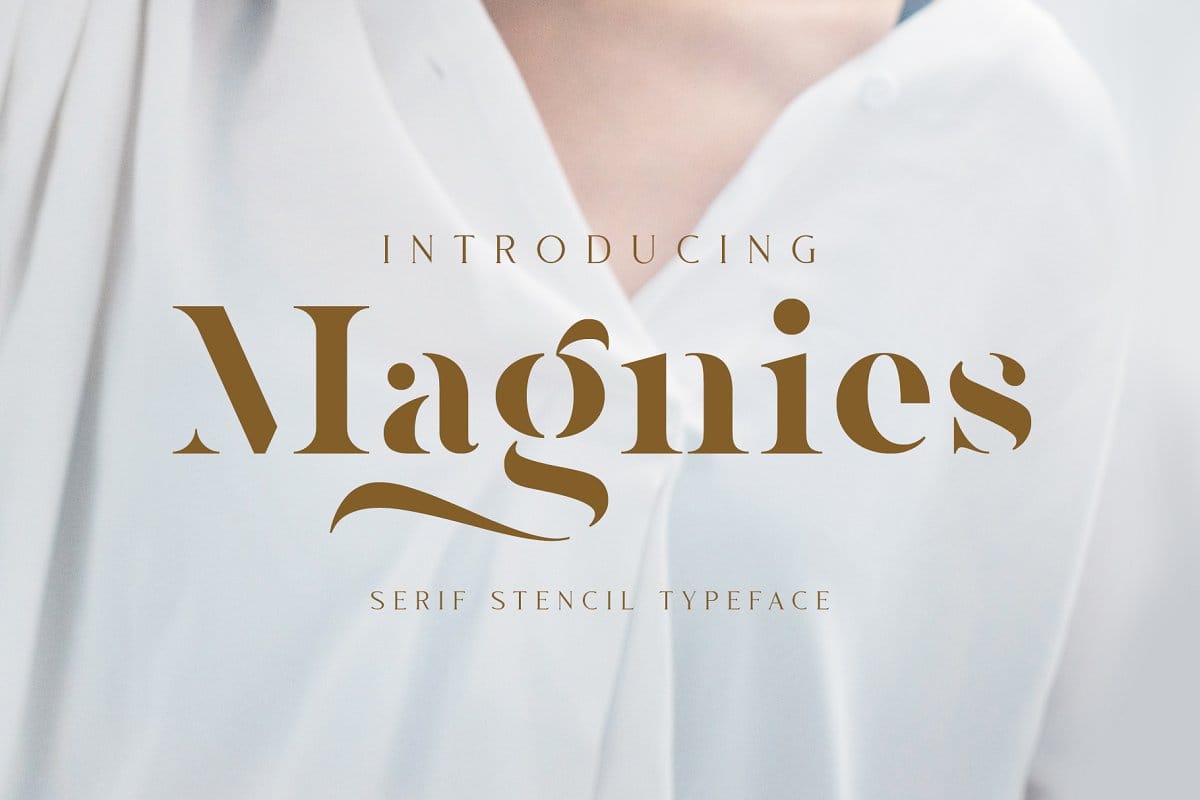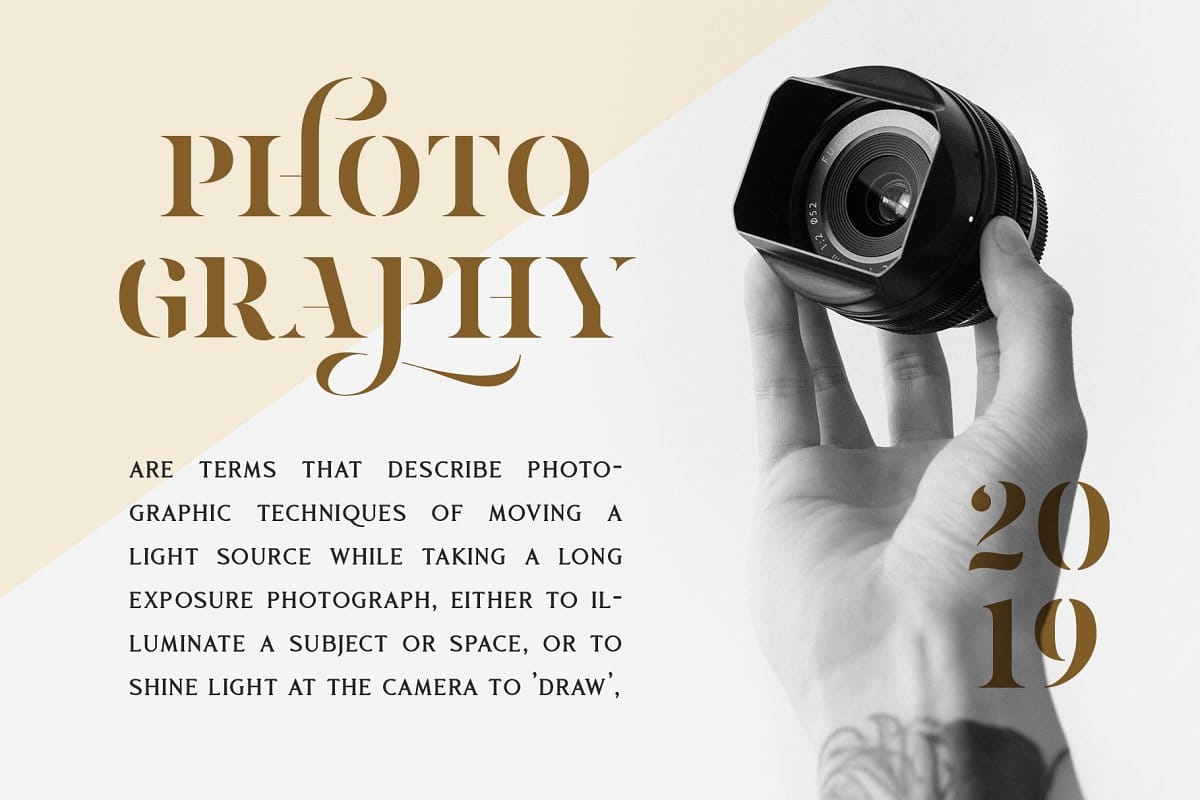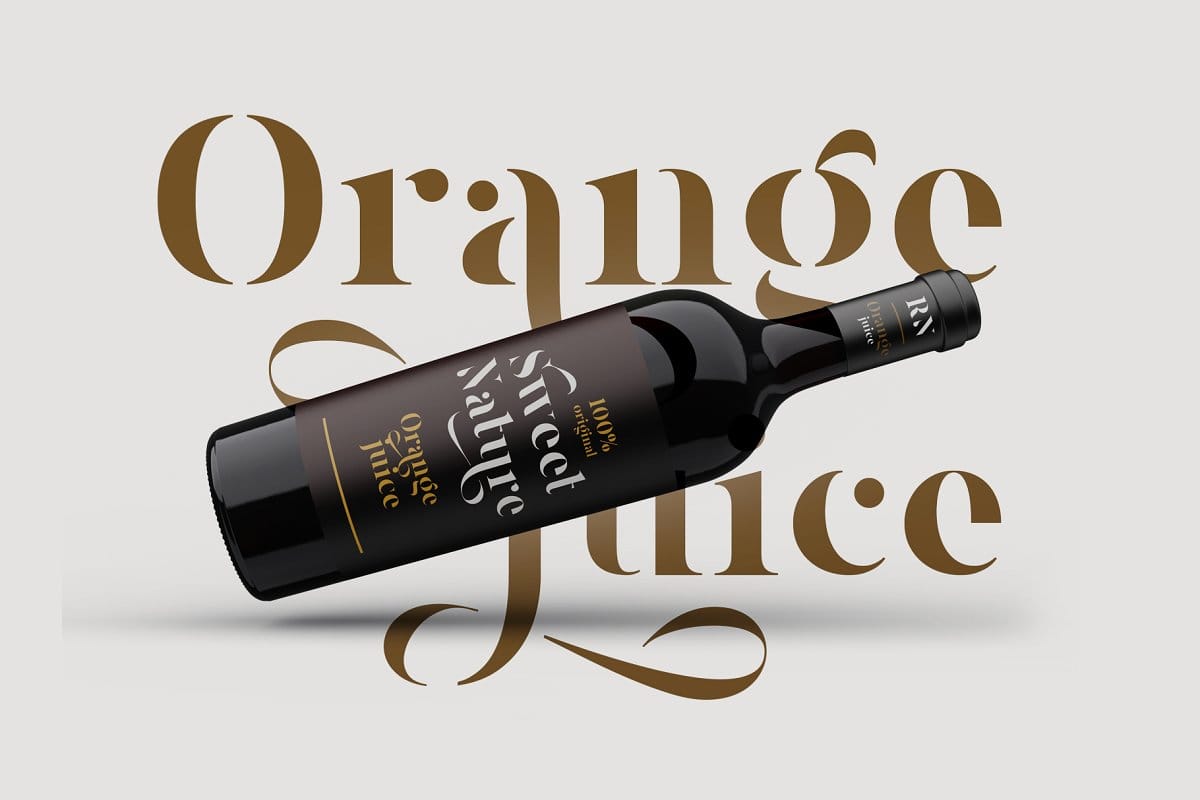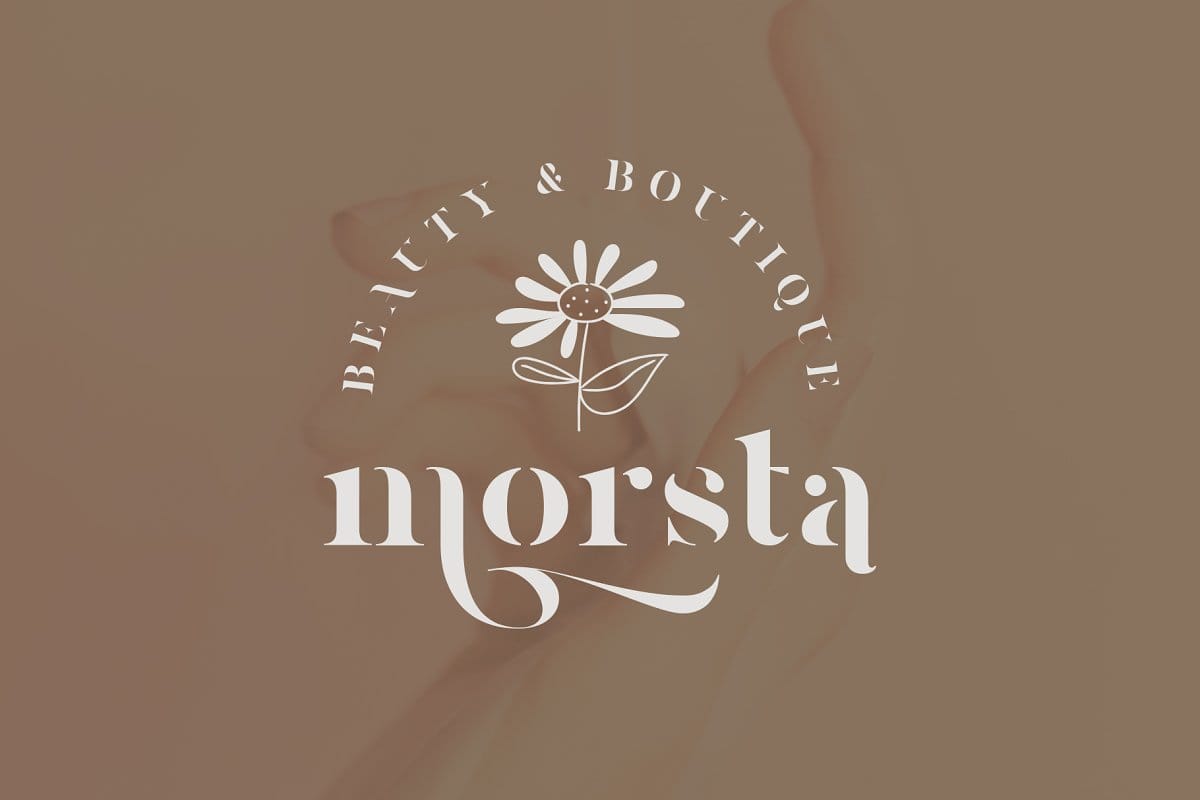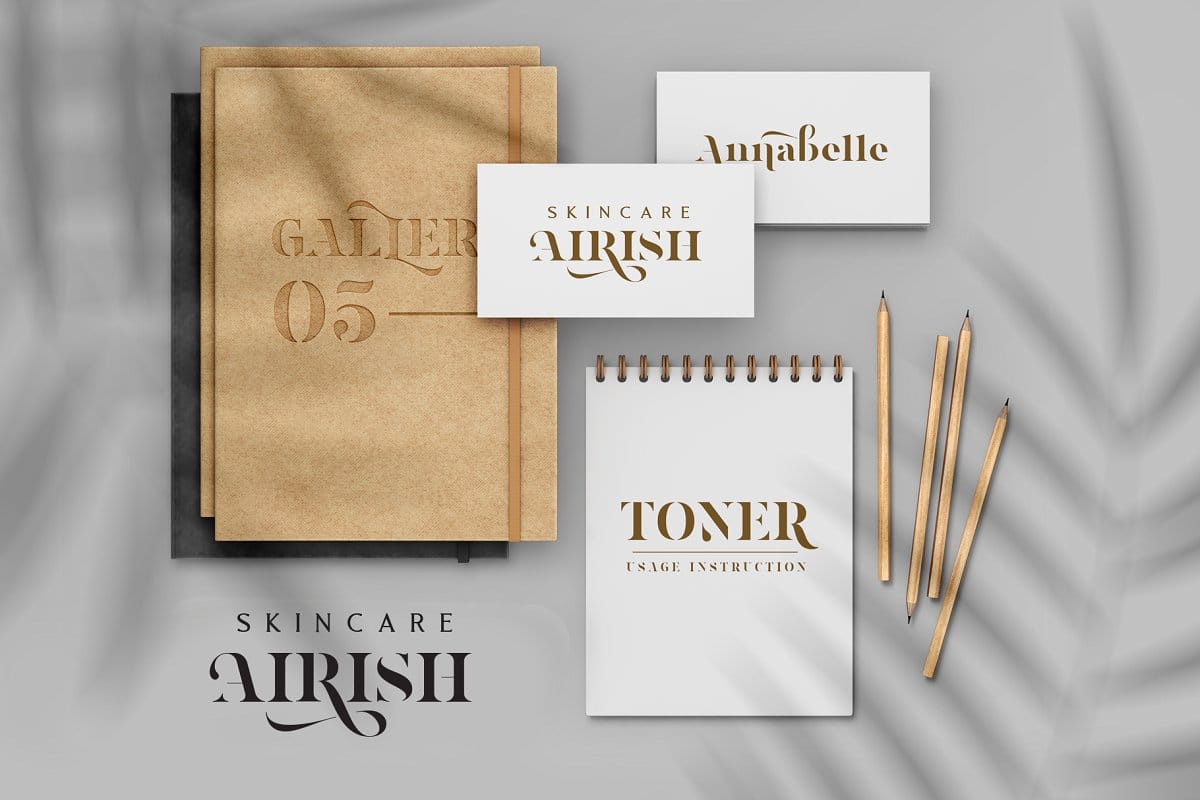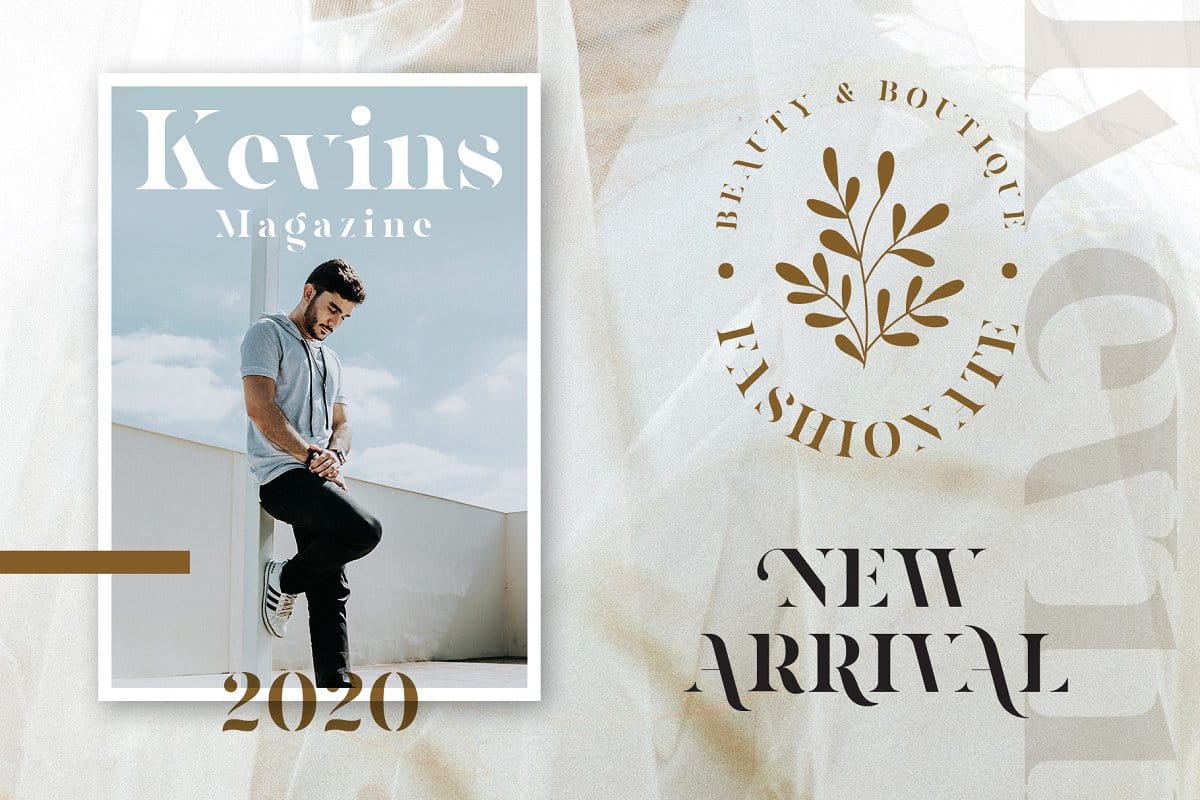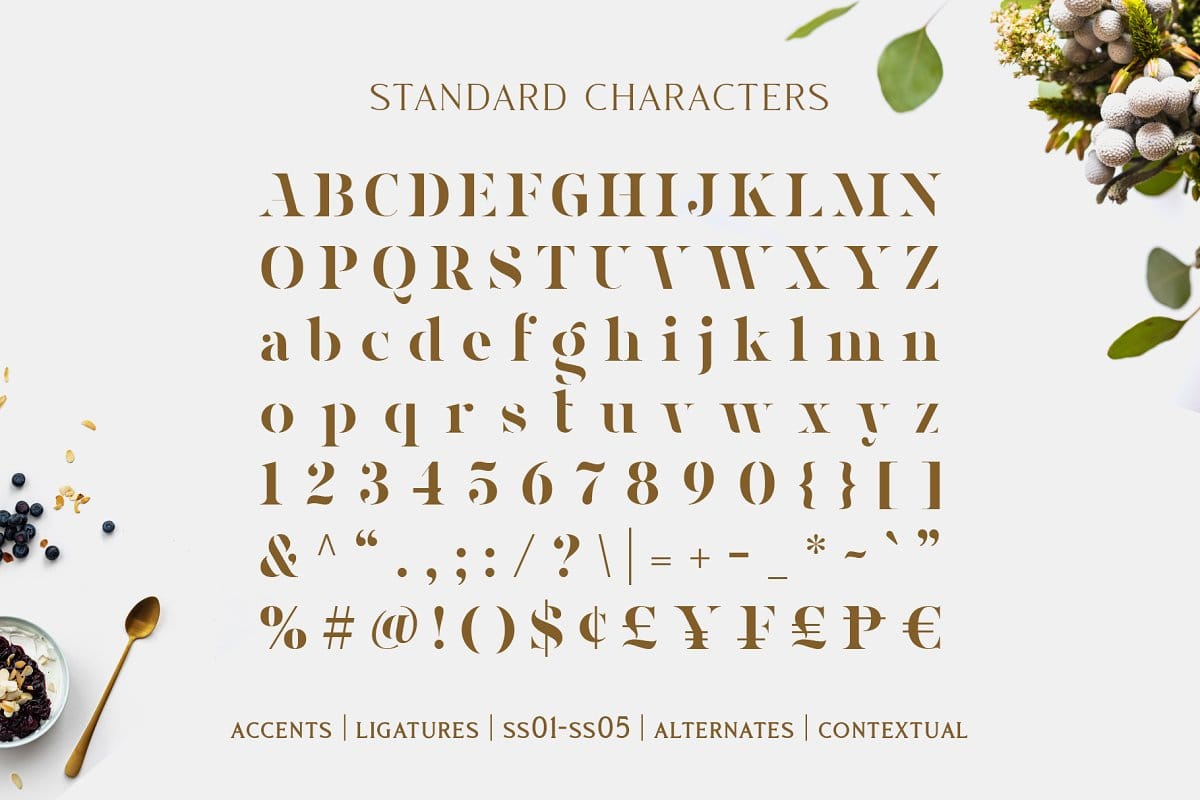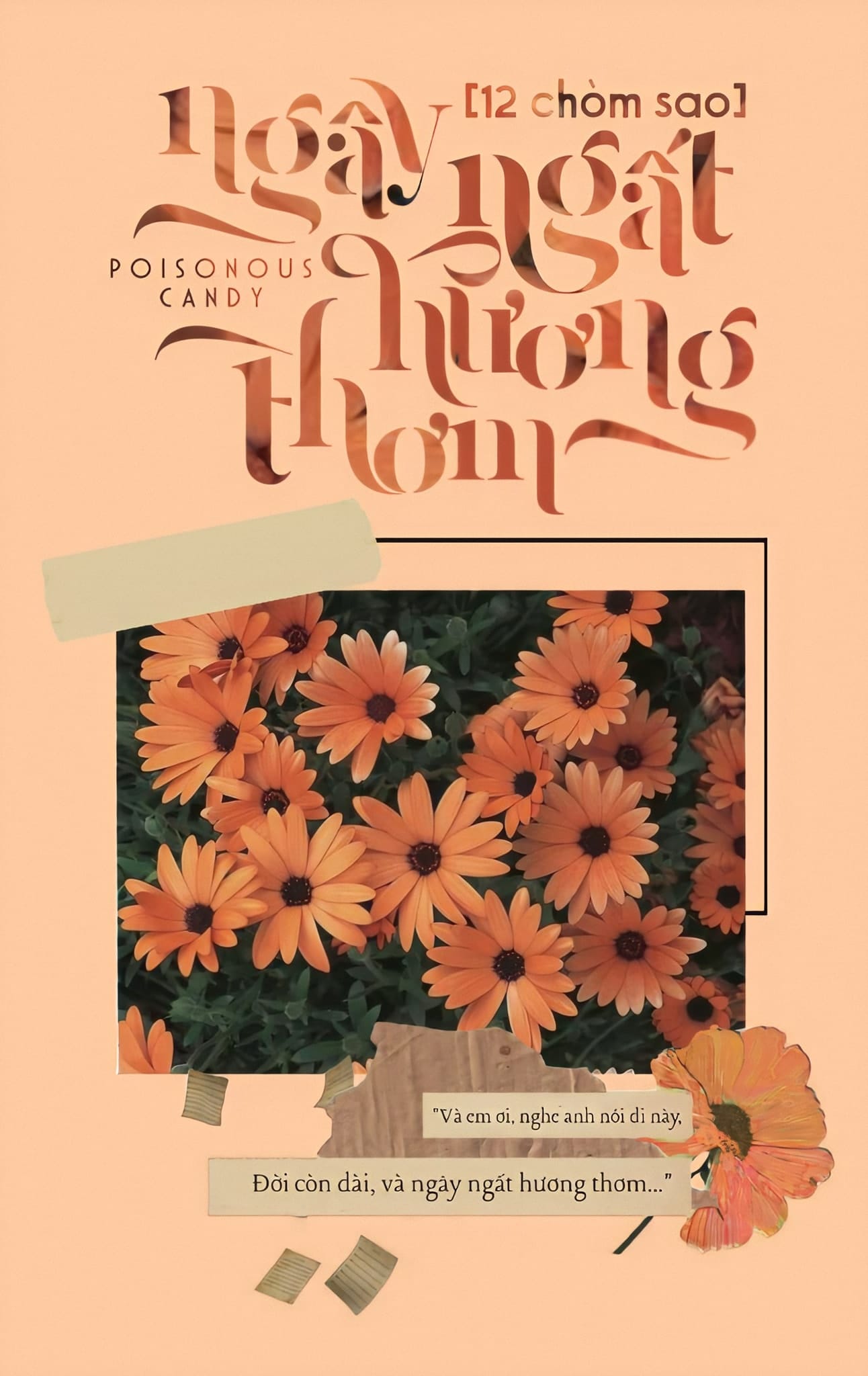
Chia sẻ miễn phí font chữ MTD Magnies Việt Hóa + font gốc Cảm nhận sự ngọt ngào với font Magnies, một phông chữ serif tối giản với vẻ ngoài bằng giấy nến sạch sẽ. Các dạng chữ cái nữ tính, hoàn hảo cho nhiều thiết kế khác nhau như biểu trưng, thời trang và trưng bày.
Magnies – Minimal Serif
được thiết kế với độ tương phản cao của các nét và cắt đường mỏng hơn để có được hiệu ứng quang học nhưng vẫn giữ được độ rõ ràng. Sự lựa chọn tuyệt vời với hơn 100 ký tự thay thế, bạn có thể tạo nhiều biến thể cho thiết kế của mình.